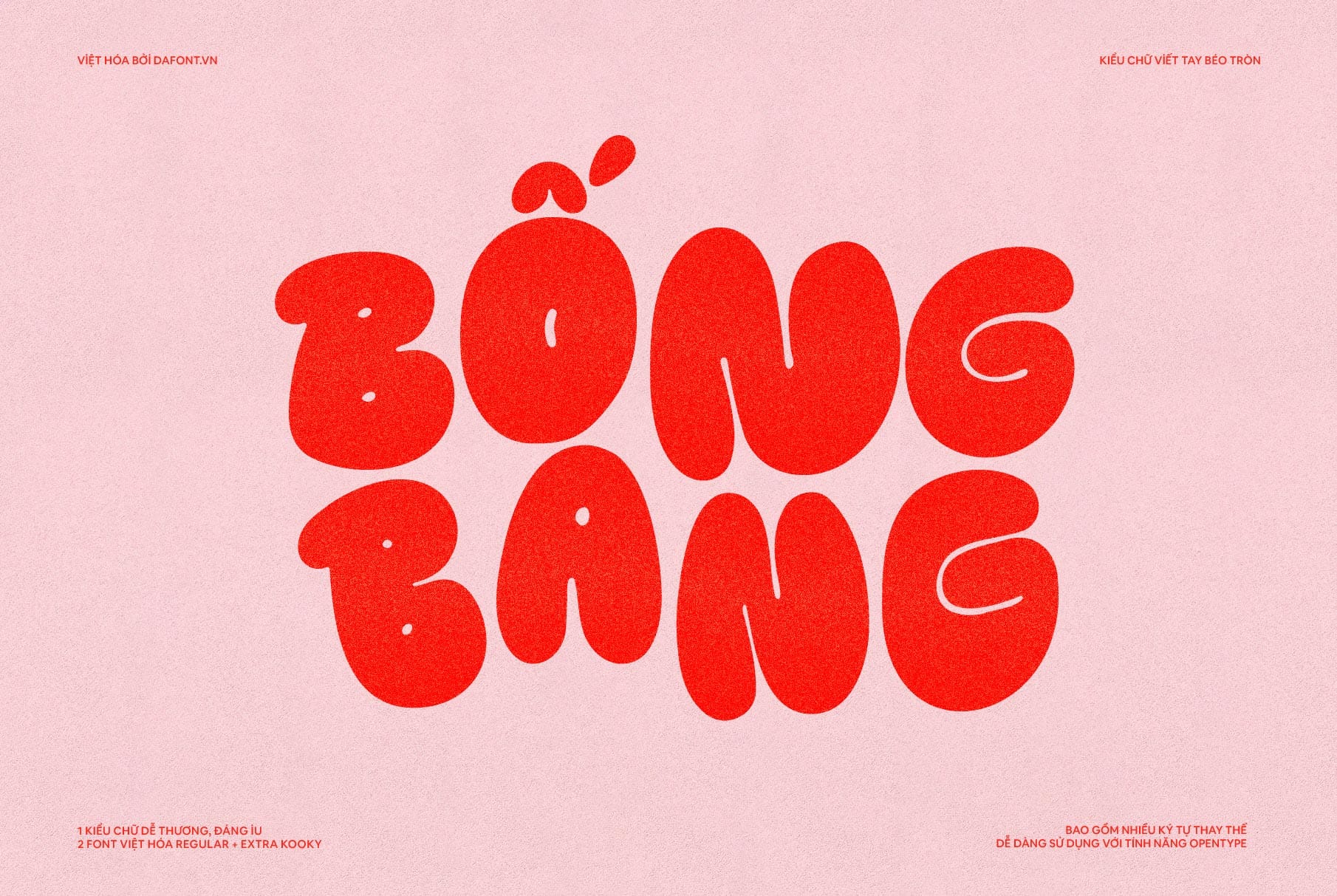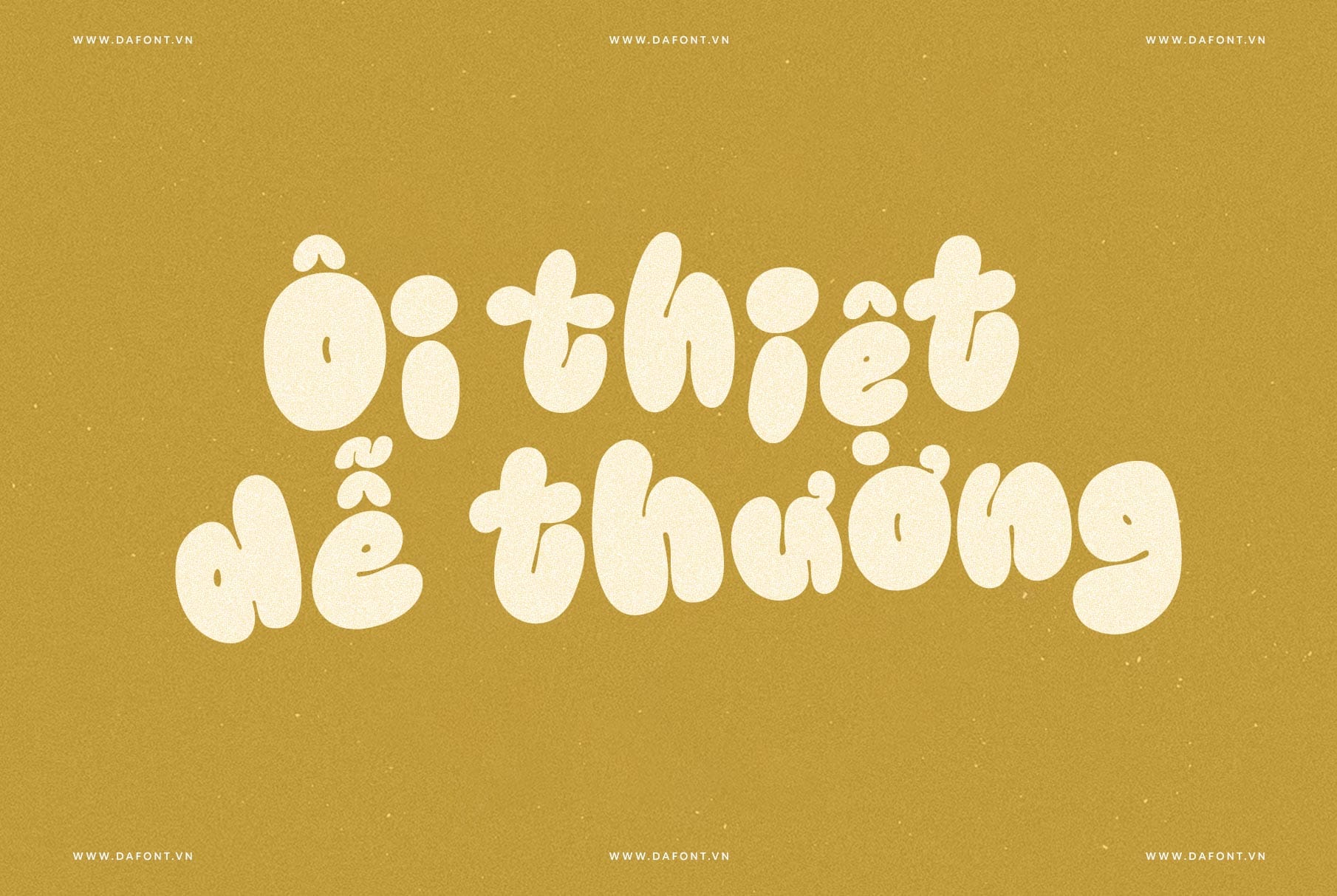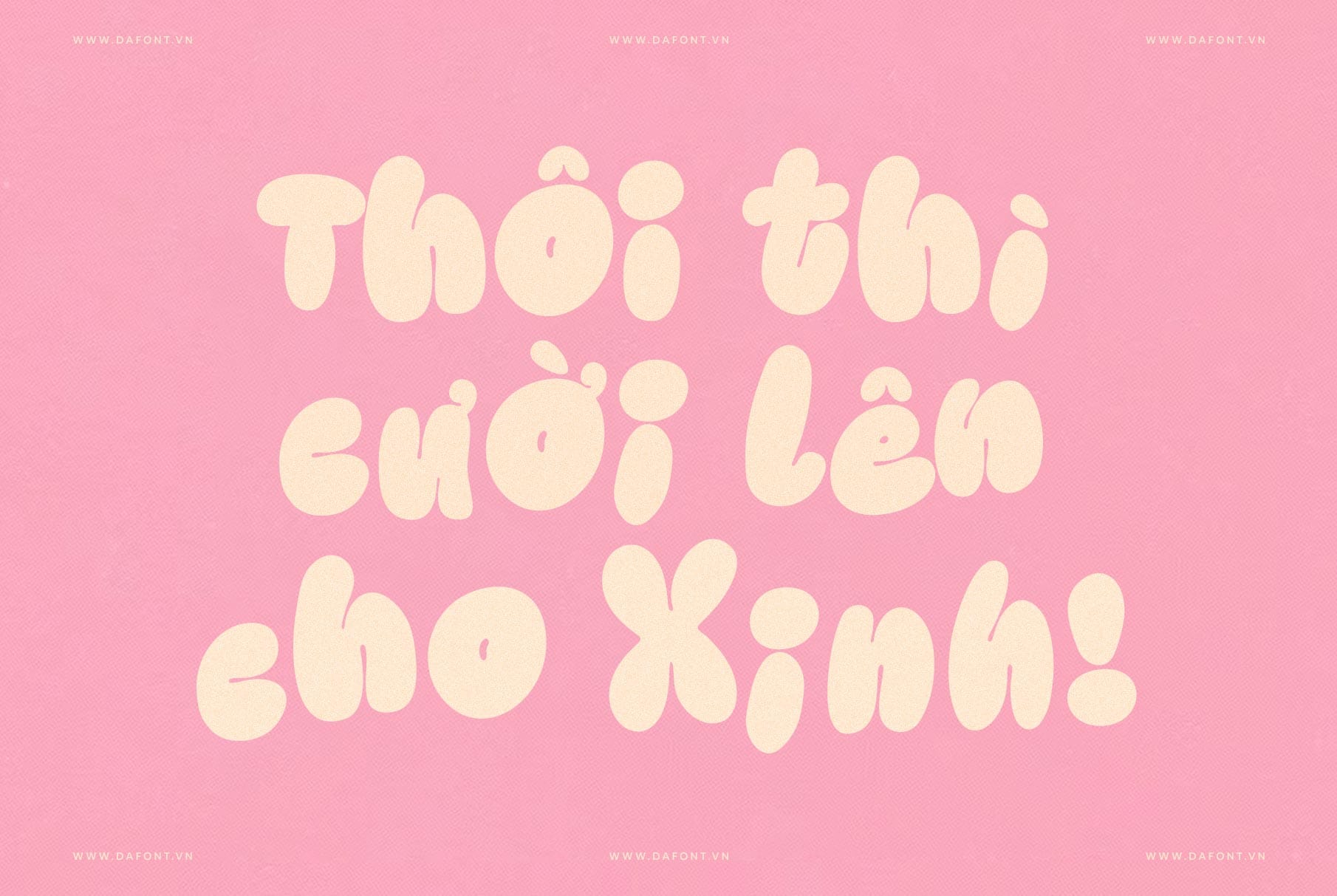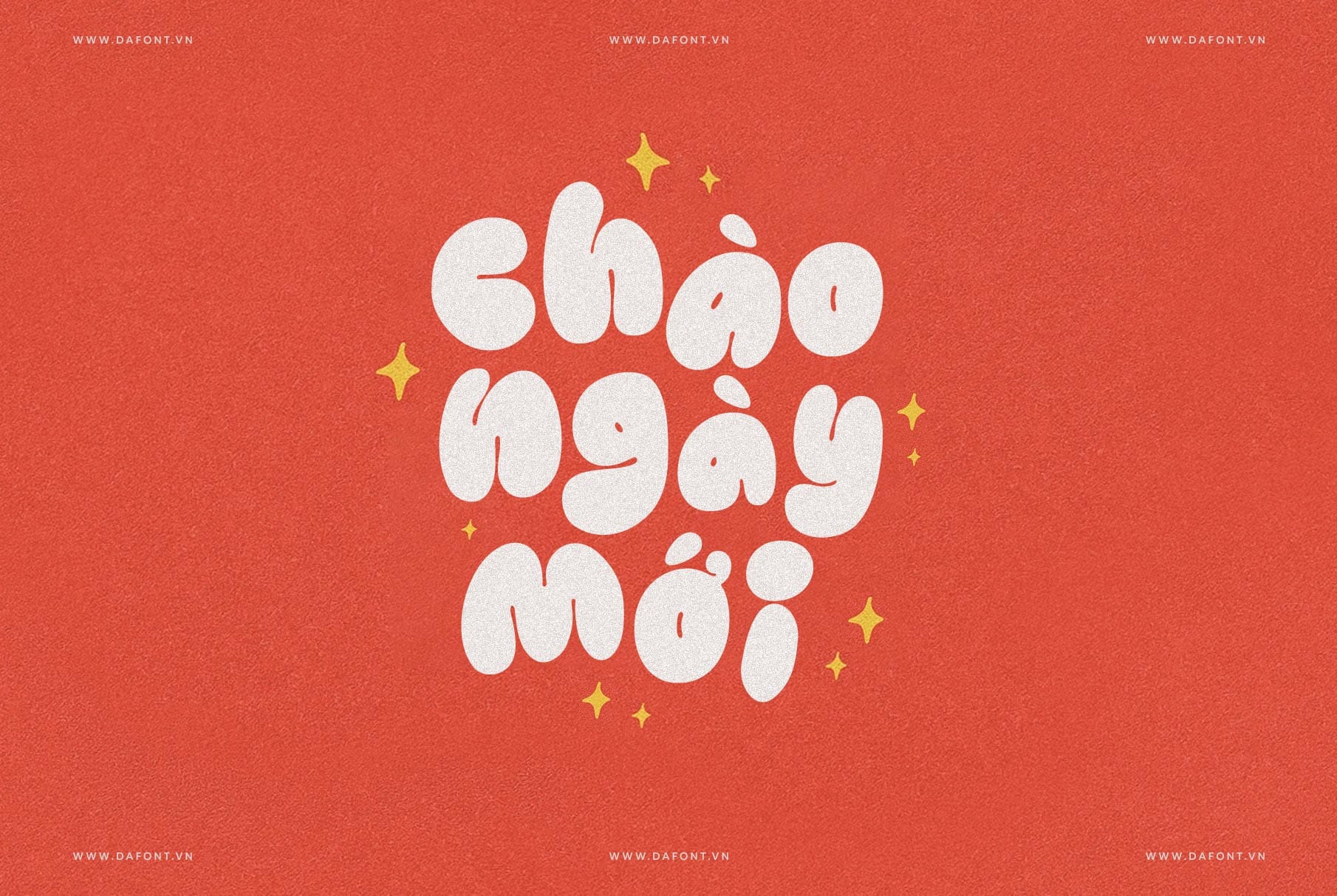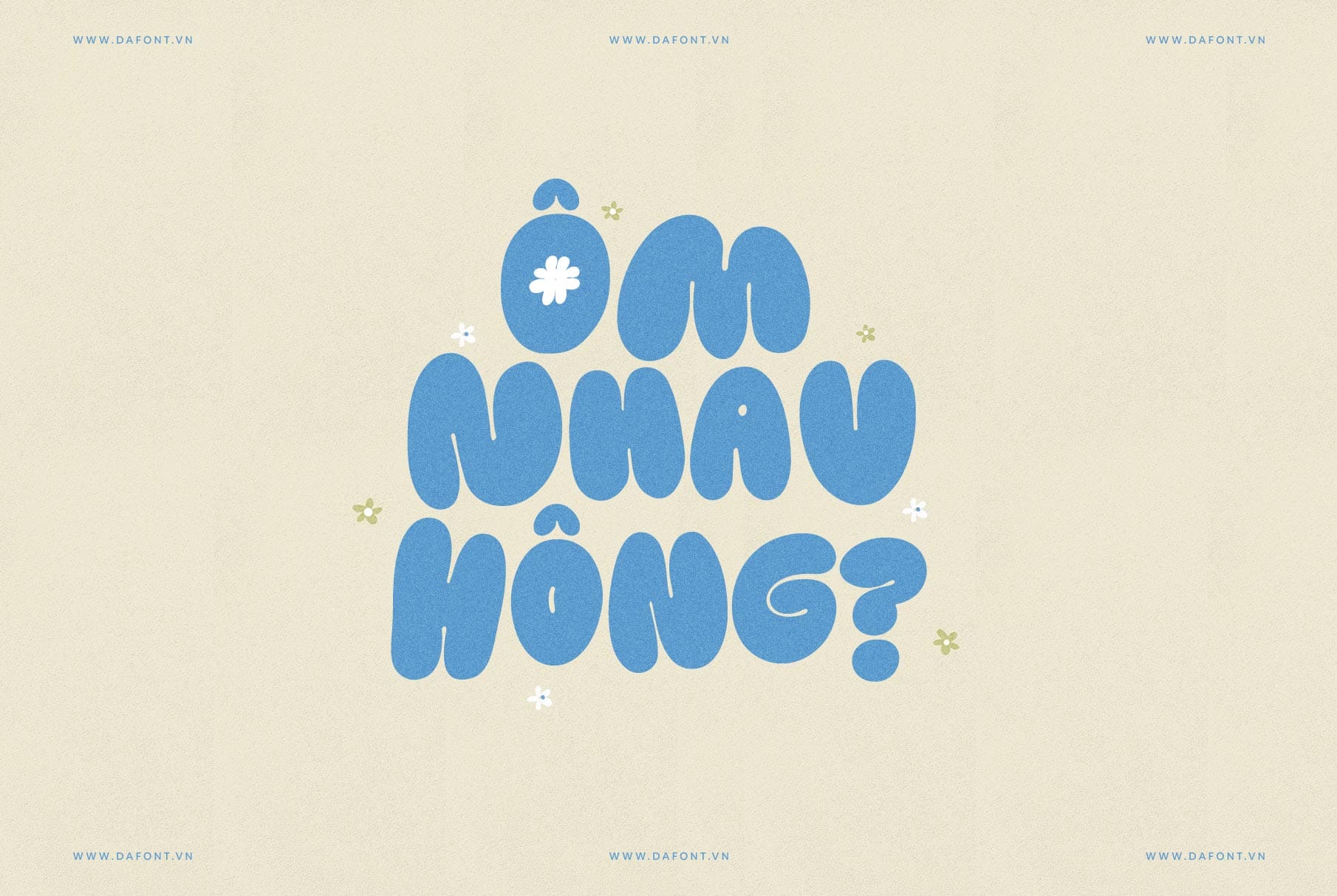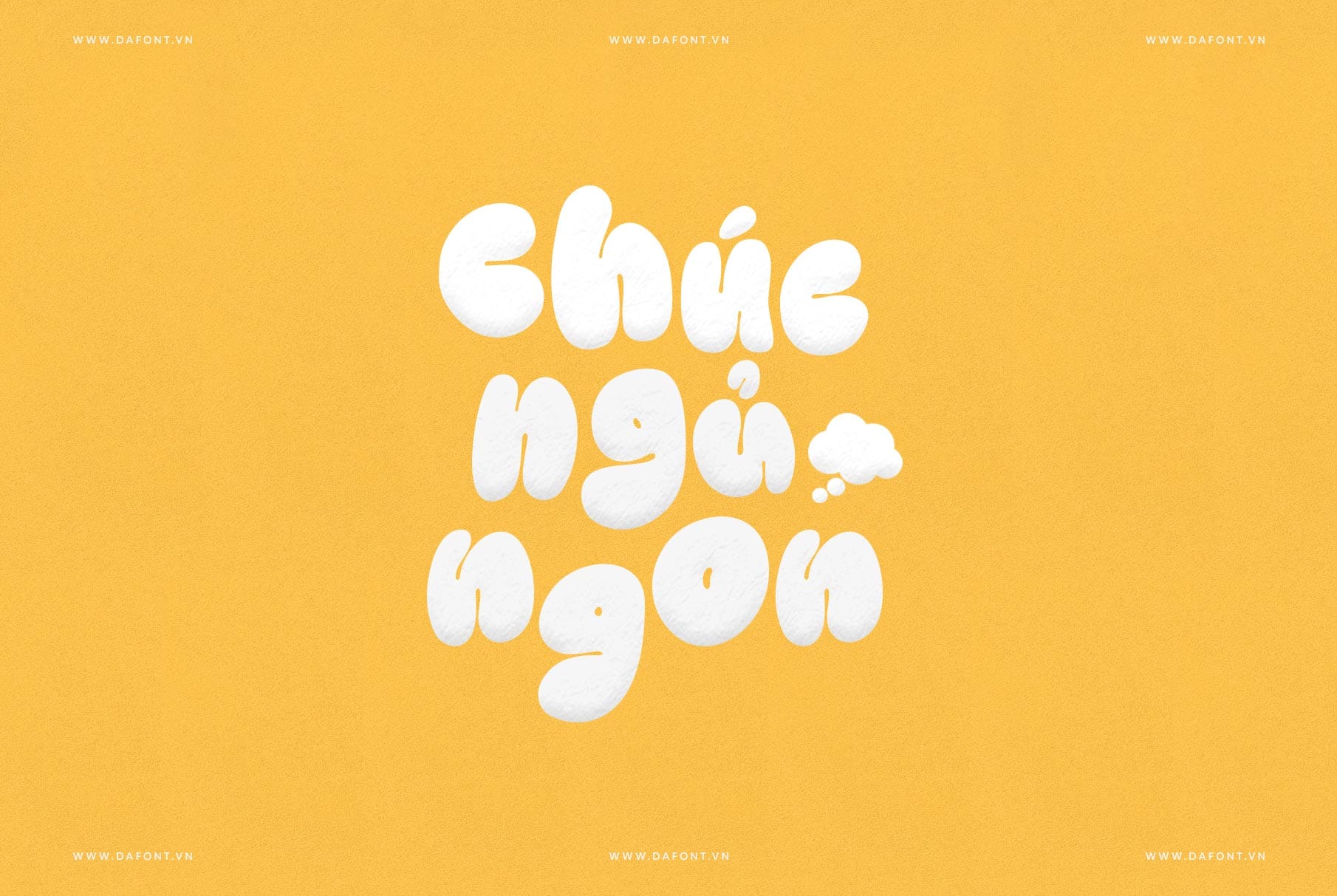
Font chữ là yếu tố quan trọng trong việc tạo độc đáo cho thiết kế, và DFVN Kooky Cloud chính là một lựa chọn tuyệt vời dành cho những ai yêu thích phong cách đồ họa bắt mắt, đậm dấu ấn tượng cá nhân.
Kooky Cloud là font viết tay được thiết kế để mang lại cảm giác dễ thương và đáng yêu. Font này có phong cách độc đáo, mang lại sự tươi mới và sáng tạo cho bất kỳ thiết kế nào.
Điểm nổi bật của DFVN Kooky Cloud
Độc đáo và tươi mới
Phong cách bubble của Kooky Cloud mang lại cảm giác vui nhộn và đậm chất thủ công. Font chữ này rất phù hợp với các thiết kế liên quan đến trẻ em, sự sáng tạo hoặc các dự án nghệ thuật.
Tính linh hoạt trong sử dụng
DFVN Kooky Cloud hoạt động hiệu quả trong nhiều thiết kế khác nhau, bao gồm logo, biển hiệu, tiêu đề, trích dẫn, và các tác phẩm nghệ thuật.
Nhiều ký tự thay thế
Kooky Cloud bao gồm toàn bộ chữ cái thay thế cho chữ hoa và chữ thường. Tất cả ký tự thay thế này cũng được Việt hóa và dễ dàng chuyển đổi qua lại bằng tính năng Opentype.
DFVN Kooky Cloud – Kiểu font viết tay béo đậm
Với phong cách độc đáo, linh hoạt và dễ sử dụng, font này chắc chắn sẽ là lựa chọn lý tưởng cho mọi dự án từ nghệ thuật đến thương mại. Hãy thử ngay và khám phá sự khác biệt mà Kooky Cloud mang lại!